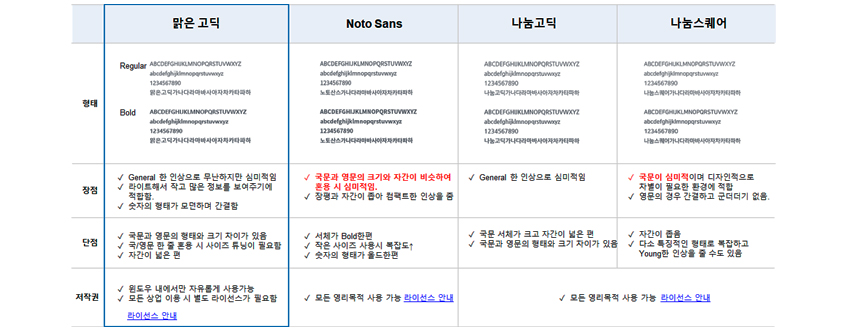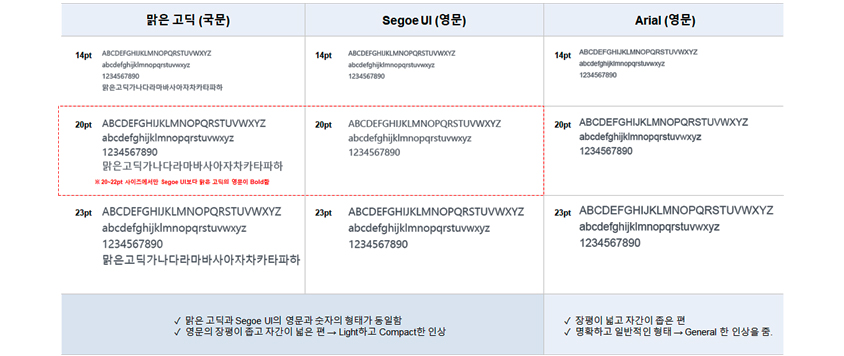
[Enterprise UX] SI 프로젝트에서는 어떤 폰트를 사용해야 할까?
이전 칼럼에서는 프로젝트 진행 시 가장 먼저 정해야 할 해상도에 대해 설명했습니다. 해상도를 정하면, 그 다음은 적합한 폰트(서체)를 선정합니다. Enterprise 업무 환경에서는 대부분 화면에 숫자와 글자, 차트 등을 이용하여 많은 정보를 전달해야 하기 때문에, 작은 글자도 잘 보이게 할 수 있는 폰트 선정이 매우 중요합니다. 그러면 보통 어떤 폰트를 사용해야 다국어에 대응하면서도 작은 글씨를 잘 보이게 하고, 크고 볼드한 타이틀까지 부담스럽지 않게 보이게 할 수 있을까요?
폰트 선정 기준
다양한 환경에서 안정적으로 적용 가능한 폰트를 선정하기 위해서는 먼저 적용 방법을 이해하는 것이 중요합니다. 폰트는 적용 방법에 따라 분류할 수 있는데, 사용자 환경과 개발 방식에 따라 저작권 확보(폰트 구매) 여부가 달라집니다. [그림 1]에서 보는 것처럼, 폰트 적용 방법은 로컬, 웹 콘텐츠, 네이티브 앱에 따라 다릅니다.
• 01 로컬 폰트 적용: 사용자가 소유한 시스템폰트 사용
• 02 웹 콘텐츠에서 호출해 적용: 다운로드 없이 웹(서버)에서 폰트를 호출해서 사용
• 03 네이티브 앱에 내장: 앱에 폰트를 내장시켜서 사용
[그림 1] 폰트 적용 방법에 따른 분류
[그림 2]는 상기 3가지 접근 방법을 좀 더 자세하게 정리한 것으로, 다수 사용환경에서 안정적으로 적용 가능한 폰트를 우선으로 선정하는 것이 중요한데 개발 방식에 대한 파악 및 라이선스 획득에 대한 사전 협의가 필요하므로 사용 전 이 부분을 꼭 점검해야 합니다.
1. 로컬 폰트 사용하기
• 특징: OS에 기본 설치되거나 사용자가 직접 설치한 시스템 폰트를 PC에서 호출해서 사용
• 장점: 가장 빠르고 안정적으로 보여짐, OS내에서의 폰트 사용시 비용 발생 없음
• 단점: 사용 가능한 폰트가 제한적임, 사용자에게 폰트 다운을 강제할 수 없음
• 총평: 사용자 PC에 기본 설치된 폰트 사용
2. 웹 콘텐츠에서 사용하기
• 특징: 웹 폰트 사용필수, 폰트 다운로드 없이 웹(서버)에서 호출해서 사용
• 장점: 다운로드 없이 다양한 폰트 사용 가능, 저작권문제에서 비교적 자유로움
• 단점: 용량이 큰 폰트의 경우 대기 시간이 발생(화면에서 텍스트가 깜빡이며 바뀌는 현상), 폰트가 사용자에게 호출 되지 않은 경우, 자동으로 차선 폰트로 대체됨, CSS font-family를 유사한 형태의 서체로 구성해야 함
• 총평: 다운로드 없이 폰트 사용
3. 네이티브 앱에서 사용하기
• 특징: 네이티브 앱에 폰트를 포함시켜 배포
• 장점: 안전하게 폰트를 보여줄 수 있음
• 단점: 개발용량이 커짐, 상용 폰트 구매 비용 발생, 개발 확장에 불리함(ex. 다국어/라이선스 비용 등)
• 총평: 강제 다운로드 후 사용
[그림 2] 폰트 사용 방법에 따른 분류
로컬 폰트 사용, 웹 콘텐츠 그리고 네이티브 앱에서 사용할 때 모든 폰트의 용량이나 장단점이 다릅니다. SI 현장은 대부분 제조, 반도체, 금융 고객인데, 대용량의 데이터를 한 번에 내려받아서 제한된 크기의 화면에 처리하는 경우가 많습니다. 저작권에 따라 분류해 보면, 가장 안전한 방법은 기본 설치된 시스템 폰트를 사용하는 것인데, 상업 용도에 자유로운 오픈 폰트 라이선스 폰트도 안전합니다. (MS Windows/Office가 설치된 환경을 기본 전제로 함)
폰트는 로컬 폰트, 웹 콘텐츠, 임베드 환경에 따라 그 용량이나 장단점이 다릅니다.
맑은 고딕
• 장점: General 한 인상으로 무난하지만 심미적임, 라이트해서 작고 많은 정보를 보여주기에 적합함, 숫자의 형태가 모던하며 간결함
• 단점: 국문과 영문의 형태와 크기 차이가 있음, 국/영문 한 줄 혼용 시 사이즈 튜닝이 필요함, 자간이 넓은 편
Noto Sans
• 장점: 국문과 영문의 크기와 자간이 비슷하여 혼용 시 심미적임, 장평과 자간이 좁아 컴팩트한 인상을 줌
• 단점: 서체가 Bold한 편, 작은 사이즈 사용 시 복잡도 증가, 숫자의 형태가 올드한 편
나눔고딕
• 장점: General한 인상으로 심미적임
• 단점: 국문 서체가 크고 자간이 넓은 편, 국문과 영문의 형태와 크기 차이가 있음
나눔스퀘어
• 장점: 국문이 심미적이며 디자인적으로 차별이 필요한 환경에 적합, 영문의 경우 간결하고 군더더기 없음
• 단점: 자간이 좁음, 다소 특징적인 형태로 복잡하고 Young한 인상을 줄 수도 있음
[그림 5] 국문 서체 비교
다음은 국내 솔루션 개발을 위한 국문 서체 정의에 대한 내용입니다.
국문 서체
설명하는 폰트는 사용자 대부분의 OS에 기본 설치된 폰트 중 선정하였고 별도의 다운로드/임베드 생략을 기본으로 생각하고 설명을 드리겠습니다. 현장에서 고객과 디자인이 가장 많이 충돌하는 지점은 폰트 사이즈입니다. 고객은 한 페이지에서 많은 양의 정보를 보기 원하는데, 그렇다고 고객의 요구를 계속 수용하다 보면 폰트 사이즈가 계속 줄어들어 오히려 가독성이 떨어지고 화면은 위계를 찾기 어려워져 바글거리는 화면이 되고 맙니다.
이렇게 고객 요구가 발생하는 경우라면 맑은 고딕을 사용해 보십시오. 고객의 요구도 만족시키면서 화면의 디자인 컨트롤이 가능해서 고객과 개발자 모두 만족시킬 수 있습니다. 맑은 고딕은 General 한 인상으로 무난하고 Light해서 작고 많은 정보를 보여주기에 아주 적합하며 숫자의 형태가 모던합니다. 국문과 영문 형태의 크기 차이도 거의 없는 장점이 있습니다. 그런데 꼭 명심해야 할 것은 윈도우 내에서는 자유롭게 사용 가능하지만, 모든 상업 이용 시 별도의 라이선스가 필요합니다. 따라서 폰트 선정 시 개발 방식에 대한 파악과 라이선스 획득에 대한 사전 협의가 반드시 필요합니다. 사용 환경과 개발 방식에 따라 저작권 확보(폰트 구매) 여부가 달라지기 때문입니다.
[그림 6] 맑은 고딕 (국문)
맑은 고딕 다음으로 많이 쓰는 폰트는 Noto Sans로서 장평과 자간이 좁아 콤팩트 한 인상을 주는 장점이 있으나 숫자 형태는 올드한 편입니다. 모든 영리 목적을 포함한 사용이 가능한 폰트입니다.
[그림 7] Noto Sans (국문)
그리고 나눔고딕과 나눔스퀘어는 General한 인상으로 심미적이고 Light한 느낌으로 국문의 크기가 다른 폰트에 비해 큰 편입니다.
폰트 선정
다음은 국내외 범용 솔루션 개발을 위한 국문/영문 폰트를 자세히 살펴보겠습니다.
맑은 고딕 (국문) vs Arial (영문)
맑은 고딕은 한글 Windows와 Office에 기본으로 적용되어 있는 한글 폰트로서 별도로 다운로드 없이 바로 사용할 수 있습니다. 다만, 해외에서는 한글 폰트가 기본으로 설치되어 있지 않습니다. Arial은 Windows와 Mac OS에서 기본으로 설치되어 있는 폰트로 영미권에서 안정적으로 보여줄 수 있는 기본 폰트로 무난한 인상을 줍니다. 크기나 형태적으로 SF pro Tex, Helvetica Neue와 흡사합니다. 반도체, 제조등 대용량의 데이터를 이용해 업무를 보는 화면의 디자인에 사용하면 좋습니다.
[그림 8] 맑은 고딕 (국문) vs Arial (영문)
맑은 고딕 (국문) vs Segoe UI (영문)
두 폰트를 사용해서 다국어를 표현한다면 알파벳 형태가 유사해 국문/영문 산출물의 동일한 인상 유지가 가능합니다. 국내외 Windows/Office 사용자에게 Segoe UI는 기본 설치된 폰트이고 영문 알파벳 자형이 맑은 고딕의 알파벳 자형과 유사해서 (약간의 자간 차이를 제외) Light하고 Compact한 형태로 모던한 인상을 줍니다.
[그림 9] 맑은 고딕 (국문) vs Segoe UI (영문)
그러면 위에서 언급한 3개의 폰트 맑은 고딕, Segoe UI, Arial을 비교해 보겠습니다.
• 맑은 고딕 (국문), Segoe UI (영문): 맑은 고딕과 Segoe UI의 영문과 숫자의 형태가 동일함, 영문의 장평이 좁고 자간이 넓은 편 → Light하고 Compact한 인상
• Arial (영문): 장평이 넓고 자간이 좁은 편, 명확하고 일반적인 형태 → General 한 인상을 줌
[그림 10] 국/영문 서체 비교
정리된 표의 국문/영문 자간의 길이를 보면 맑은 고딕과 Segoe UI의 영문과 숫자 형태가 동일해서 시스템 구축할 때 적용하면 좋고 두 폰트가 적용된 사이트가 Microsoft인데 국/영문 사이트를 비교해보면 레이아웃과 텍스트 길이까지 비슷해서 일관성 있는 인상을 줍니다.
Microsoft
자체 개발한 폰트를 사용하고 있으며, 영문 사이트는 Segoe UI, 국문 사이트는 맑은 고딕을 사용합니다. 국문/영문 모두 동일한 레이아웃을 갖고 있고 폰트의 느낌도 일관성 있습니다.
[그림 11] Microsoft 사이트 국/영문 서체 비교
아래 그림은 Apple과 삼성전자 사이트의 폰트 비교 입니다. Apple은 자체 개발 폰트를 사용하고 영문 SF pro Text+ 한글 SF pro Text를 적용했는데 폰트 자간부터 모양까지 일관성 있게 애플 제품의 가진 대칭 정방향 느낌까지 폰트에 적용되어 웹사이트에서 애플 제품의 철학의 방향이 적절한 폰트사용으로 같은 방향성을 고객이 느끼게 해줍니다. 삼성전자 역시 자체 개발 폰트를 사용하고 있고 영문 사이트는 Samsung One latin Web, 한글은 삼성긴고딕 웹 light폰트가 적용되어 있습니다. 삼성전자는 Apple과는 다르게 글로벌과 로컬의 디자인 레이아웃이 다른 특성을 반영하고 있습니다.
[그림 12] Apple/Samsung 사이트 국/영문 서체 비교
위에서 글로벌 3사가 어떻게 자사 웹에 국문과 영문 폰트를 적용하고 있는지 살펴 보았습니다.
폰트 사용 가이드
지금부터는 선정한 폰트를 실제 현장에서 어떻게 사용하는 것이 바람직한지 적용 팁에 대해서 설명하겠습니다. 설명할 폰트는 작은 사이즈 폰트 컨트롤이 가능해서 대량의 정보를 보여주기에 접합한 한글 맑은 고딕과 영문 Segoe UI입니다.
1. 영문에서 국문으로 단순 변경하는 경우
국내외용 동시 개발 시 단순히 언어 변환만 하면 폰트 사이즈가 상이해 보일 수 있습니다. 아래 [그림 13]은 언어 변환만 했을 때입니다.
[그림 13] 국/영문 단순 변환 시 폰트 크기가 상이해 보이는 현상
국/영문 길이 차이는 세부 튜닝이 필요한데요. 영문에서 국문으로 단순 변경하는 경우, 대략 20pt 이상 크기에서는 영문 (30pt)보다 국문 (28pt)을 작게 하면 심미적으로 보입니다.
[그림 14] 국/영문 단순 변환 시 폰트 크기 적용 팁
2. 국/영문을 한 줄에 혼용하는 경우
본문 폰트의 크기가 20pt 이상인 경우에는 영문 기준으로 국문을 작게 튜닝해야 심미적으로 보이고, 20pt 이하는 차이가 미미하므로 별도의 튜닝 없이 사용 가능합니다.
[그림 15] 국/영문이 한 줄에 혼용하는 경우, 폰트 크기 적용 팁
3. 국/영문 자간을 조정해야 하는 경우
[그림 16] 비교와 같이 가독성을 위한 자간 조정을 해야 하는데 자간 조정은 국문을 기준으로 해야 안정적으로 보입니다.
[그림 16] 국/영문 자간 조정 팁
다음은 베트남어를 예로 들어 다국어 적용 디자인 시 참고사항에 대해서 설명하겠습니다.
베트남어의 경우 영어보다 글자 높이가 높기 때문에 그것을 고려해서 행간을 여유 있게 잡아야 합니다.
[그림 17] 베트남어, 영문 글자 높이 비교
동일 문장의 경우 베트남어가 영어보다 글자 수가 많기 때문에 글줄의 개수를 고정(텍스트 세로 영역 고정)할 때, 베트남어는 말 줄임 처리로 해결해야 합니다. ([그림 18] 사진 내 텍스트 배치로 글줄 확장이 어려울 경우) 정보의 양을 동일하게 하려면 줄 바꿈 처리로 세로 영역을 확장해야 합니다. ([그림 19] 사진 아래 텍스트 배치로 글 줄 추가 가능한 경우)
[그림 18] 동일문자 영어 베트남어 글자수 비교 (1)
[그림 19] 동일문자 영어 베트남어 글자수 비교 (2)
위에서 말했듯이 베트남어가 영어보다 글자 수가 많기 때문에 카드의 너비는 고정하되 높이는 가변으로 글줄의 확장에 따라 카드 높이도 확장되는 구조로 디자인/개발해야 합니다.
[그림 20] 동일문자 영어 베트남어 글자수 비교 (3)
텍스트의 정렬(좌/우/센터)은 다국어에 영향을 받지 않고 모두 가능합니다. 단, 이 경우 테스트의 좌우 너비를 반드시 지정해 줘야 글자 수 증가로 인해 서로의 정보가 겹치는 일이 없게 됩니다. 그리고 좌측 정렬하여 텍스트나 이미지의 좌우 영역 너비는 고정하고 세로 영역은 자유롭게 확장할 수 있는 디자인을 하면 대부분 문제가 발생하지 않습니다.
[그림 21] 다국어 텍스트 정렬
좌우 영역 너비를 고려해 다국어 레이블 길이를 제한(ex. 메뉴명)헤야 하는데 디자인적으로는 레이블 길이에 따라 좌우 너비가 확장 가능한 디자인이 좋습니다.
[그림 22] 좌우 영역 너비를 고려해 다국어 레이블 길이를 제안 (ex. 메뉴명)
마무리를 하며
다국어를 디자인할 때는 대체로 사진, 텍스트, 색 면, 소량의 아이콘, 심플한 형태의 버튼으로 구성해야 다국어 대응에 무난합니다. 또한 다양한 이펙트와 비정형의 도형들은 배경 효과 정도로 최소 적용해야 인지 오류를 예방할 수 있습니다. 특히, 다국어 변경 시 텍스트 글줄이 늘어날 것을 고려해, 텍스트 영역 높이를 고정하기보다는 텍스트 영역 높이를 유연하게 확장하는 것이 좋으며, 부득이 영역 높이를 고정해야 할 경우 영역 내 스크롤을 추가할 수 있으나 권장사항은 아닙니다. 영역을 고정하고 텍스트를 말 줄임 처리할 경우, 필수 노출 정보가 가려 질 수 있으므로 대체로 권장하지 않습니다. 하나의 디자인으로 다국어에 대응할 때 이 부분을 꼭 유념해서 디자인하시면 다양한 개발 환경에서 발생할 수 있는 이슈들을 예방할 수 있습니다.
폰트 선정은 프로젝트 현장에서 무척 중요합니다. 프로젝트 중간에 폰트를 교체하는 것은 어마어마한 시간과 비용을 낭비할 수 있으므로 폰트 선정에 신중해야 합니다. 폰트의 몇 가지 장단점을 사전에 파악하고 적절한 폰트를 사용한다면 오류 없는 디자인 진행이 가능합니다.
이번 아티클에서는 SI 현장에서 (제조, 물류, 반도체, 빅데이터 등) 여백 없이 빽빽하게 정보를 무조건 많이 볼 수 있게 넣어달라는 고객이 종종 있습니다. 하지만, 그렇게 되면 오히려 정보가 보이지 않게 되는 어려움이 발생할 수 있으니 적절한 폰트 선정 및 디자인 적용으로 대응이 가능하다는 것에 대해서 설명했습니다.
다음 글에서는 위의 내용과 같은 고객의 요구를 수용하기 어려운 디자인 환경에서 어떻게 이 부분을 설득하고 해결해야 할지에 대해 설명하겠습니다.